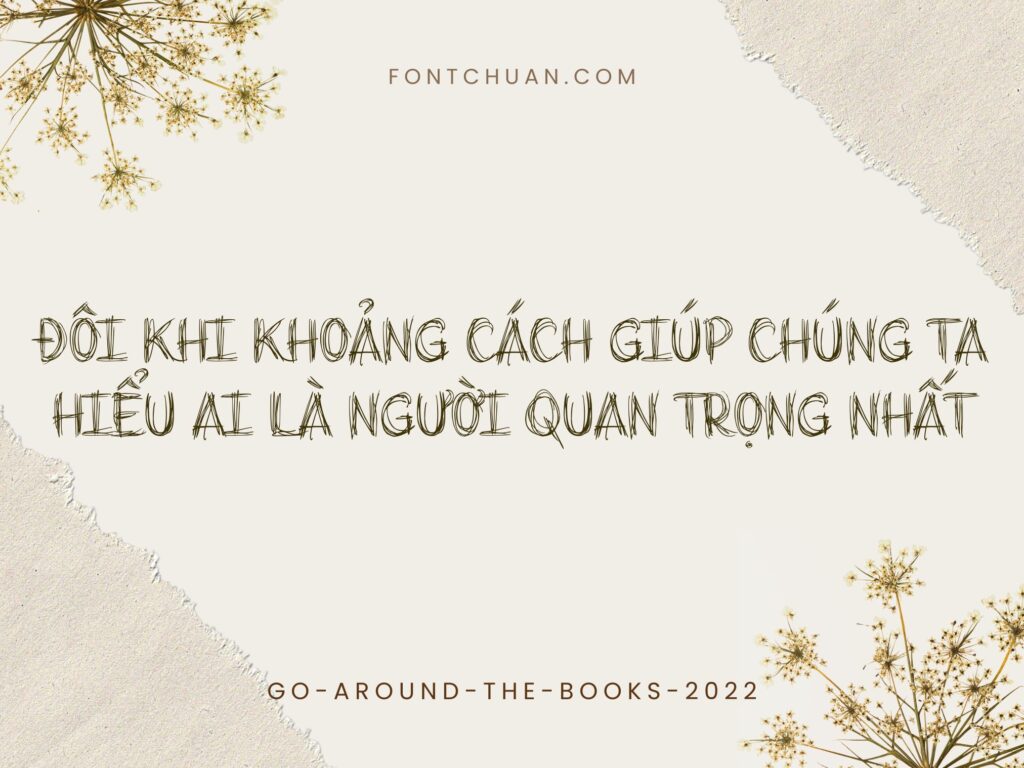
Font Go Around The Books 2022 Font Tiếng Việt
Go around the books 2022 là một phông chữ viết tay độc đáo, được thiết kế bởi Poemhaiku. Đây cũng được xem là một dạng Font chữ Halloween nhờ phong cách vẽ tay với các nét chữ không đều, tạo cảm giác nghệ thuật và sáng tạo. Phiên bản 2022 đã được cải tiến so với phiên bản 2014, với nhiều ký tự thay thế hơn, giúp người dùng có thêm lựa chọn trong thiết kế. Để sử dụng đầy đủ các ký tự thay thế này, bạn cần sử dụng phần mềm như Adobe Illustrator. Phông chữ này được cung cấp miễn phí cho mục đích cá nhân; nếu cần sử dụng trong dự án thương mại, người dùng nên liên hệ trực tiếp với tác giả để biết thêm thông tin.